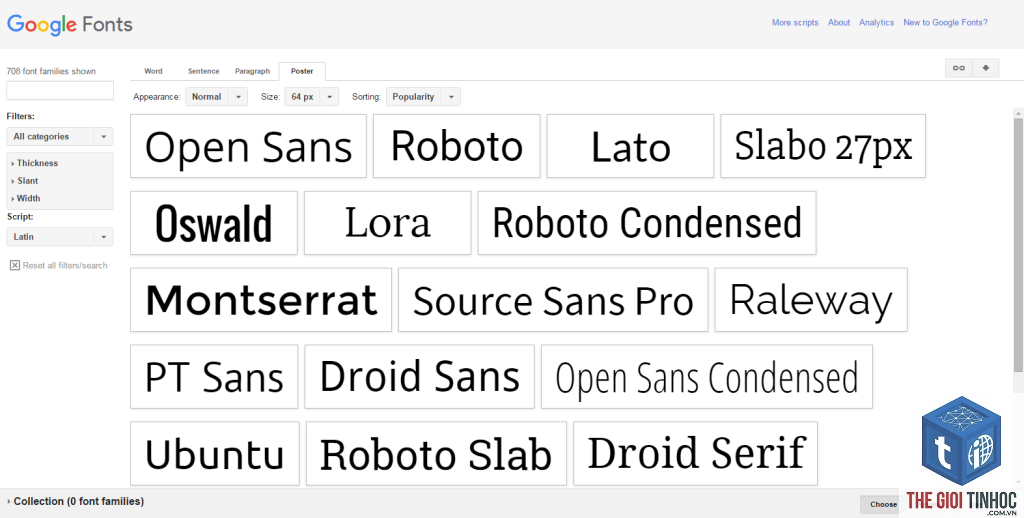
Google Fonts WordPress là gì và tại sao bạn cần quan tâm?
Google Fonts là bộ sưu tập hơn 1.400 font chữ mã nguồn mở miễn phí do Google phát triển. Khi kết hợp với WordPress,
Có nên dùng Google Fonts cho website thương mại điện tử không?
Hoàn toàn có thể, nhưng cần chọn font chữ rõ ràng, dễ đọc và tối ưu tốc độ. Font sans-serif như Open Sans, Roboto là lựa chọn phổ biến cho website bán hàng vì tính chuyên nghiệp và khả năng đọc cao.
Kết luận
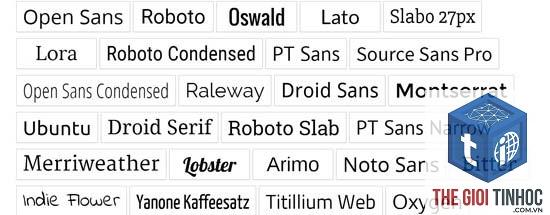
Google Fonts WordPress là công cụ mạnh mẽ giúp nâng cao thẩm mỹ và trải nghiệm người dùng cho website. Việc lựa chọn phương pháp tích hợp phù hợp phụ thuộc vào trình độ kỹ thuật và yêu cầu cụ thể của từng dự án. Người mới nên bắt đầu với plugin hoặc theme có sẵn, trong khi người có kinh nghiệm có thể tối ưu thủ công để kiểm soát tốt hơn.